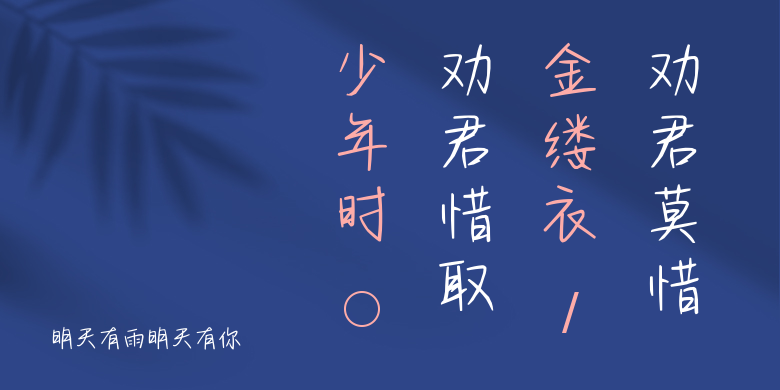
明天有雨明天有你
明天有雨明天有你,这款字体结构工整、笔画清晰,兼顾美观与易读性,适用于标题、正文、海报、包装、LOGO 等多种场景。字形优雅稳定,风格百搭耐看,适配日常排版与创意设计,让文字呈现更舒适、更具质感。明天有雨明天有你一笔一画,皆是细节,以均衡的比例、流畅的线条打造舒适视觉体验,字形端正大气,风格简约现代。无论是商业设计、品牌宣传还是日常排版,都能轻松驾驭,让文字更有格调与力量。明天有雨明天有你字体下载。